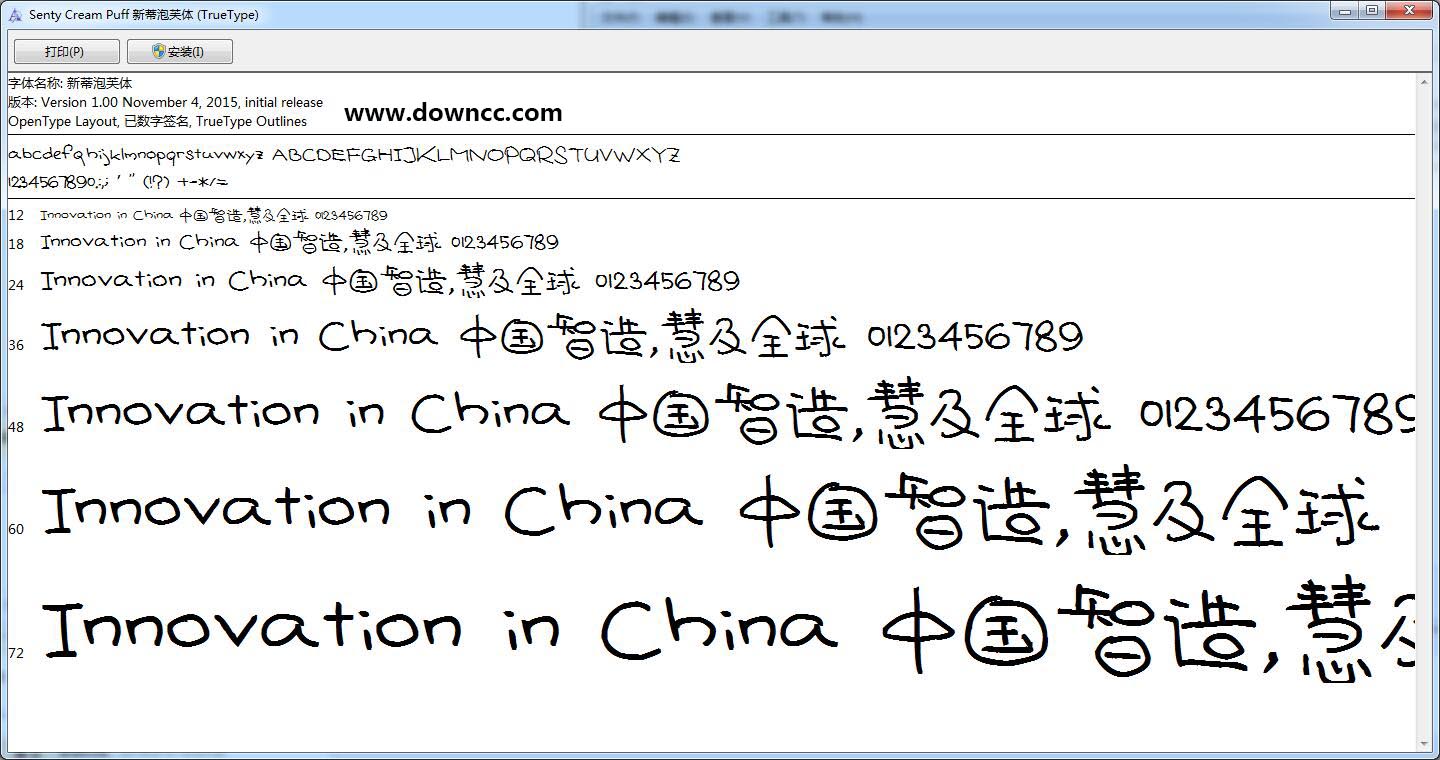
新蒂泡芙體ttf
新蒂泡芙體是一款具有可愛卡通風(fēng)格的字體應(yīng)用。改字體支持中文、英文、數(shù)字等輸入,還可以適用于設(shè)計行業(yè)使用!喜歡的用戶可以來綠色資源網(wǎng)下載使用!
新蒂泡芙體(SentyCreamPuff)是一款應(yīng)用于設(shè)計方面的中文簡體漢字,該字體筆畫非常細(xì)膩,整體效果為卡通風(fēng)格,且字庫完整,覆蓋常用簡體、繁體漢字、拉丁字母、數(shù)字等,可以適用于書報刊標(biāo)題,廣告設(shè)計、印刷、商標(biāo)注冊、名稱、包裝等!